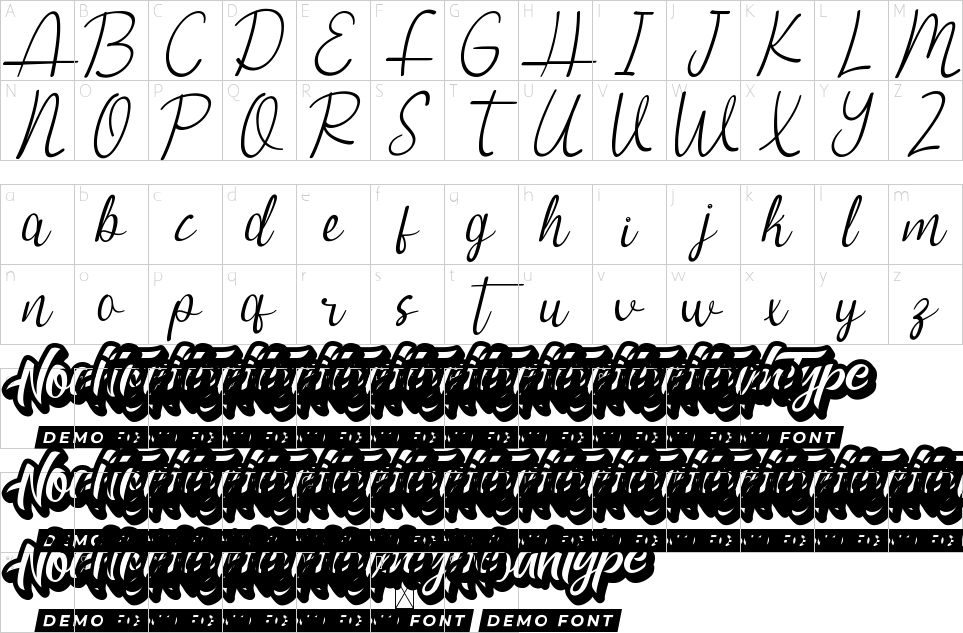
Aussie House Font
Descubra a fonte ‘Aussie House’ para seu projeto no Windows e Mac. Esta fonte foi projetada por noahtype e já foi baixada por 2,038 usuários. ‘Aussie House’ traz um charme casual e alegre ao seu design, com um toque australiano que vai agradar tanto os designers quanto os criadores de conteúdo. Com uma aparência fácil de ler e uma variedade de opções de estilo, esta fonte é perfeita para aqueles que buscam um estilo de escrita leve e descontraído. Baixe ‘Aussie House’ agora e adicione um toque australiano a seu próximo projeto.